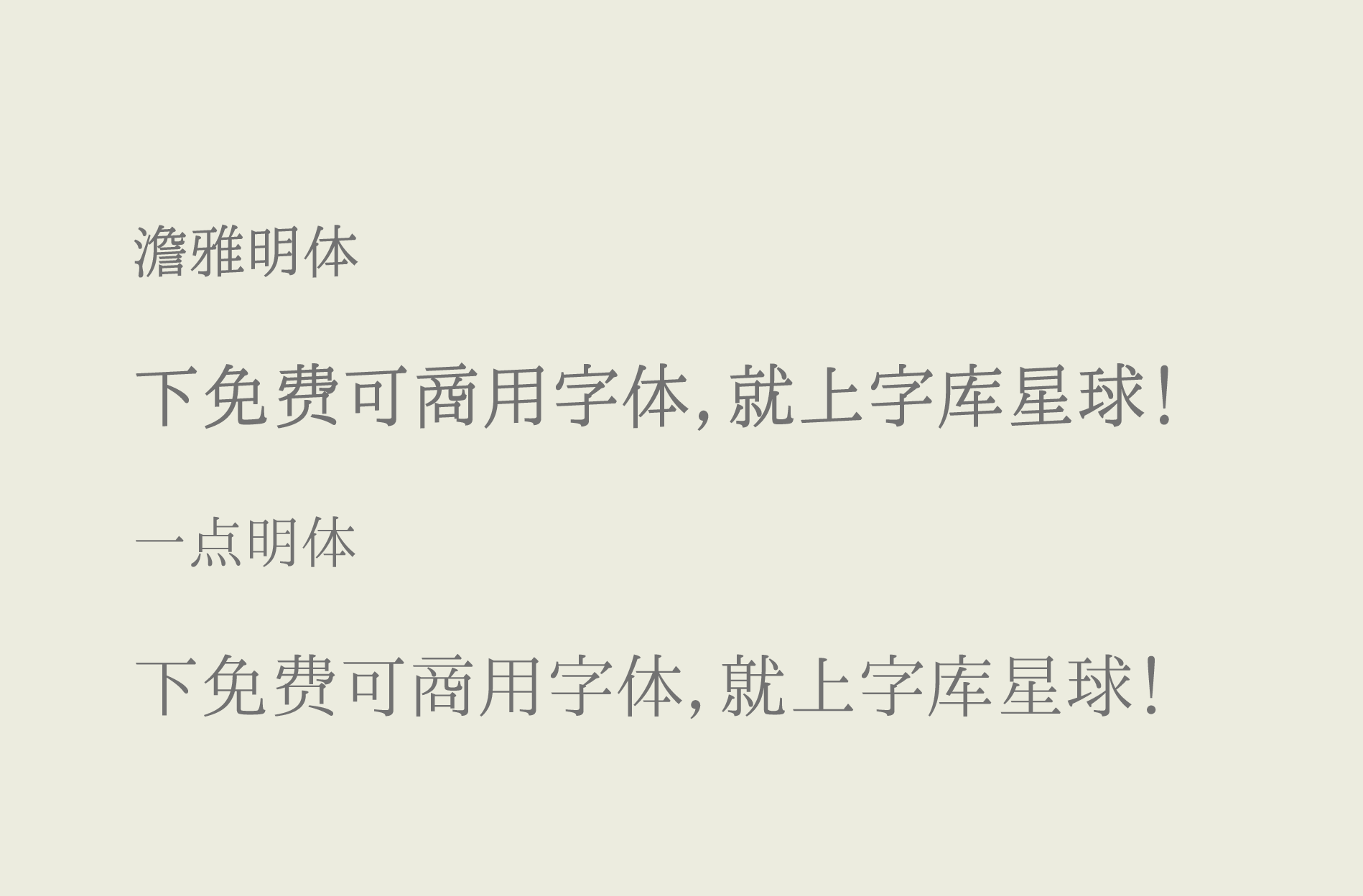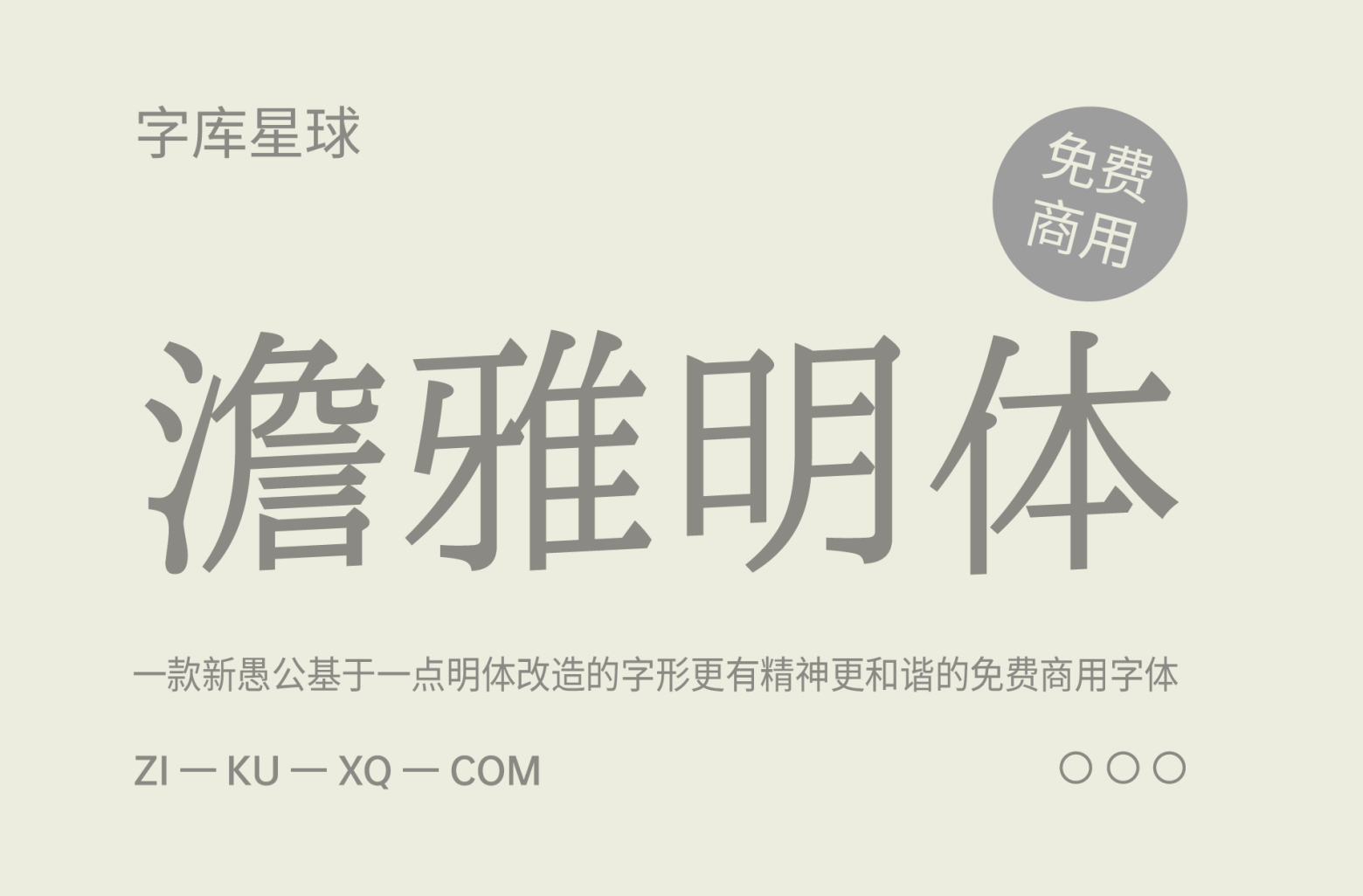
澹雅明体
澹雅明体是一款@新愚公基于一点明体改造的字形更有精神更和谐的免费商用字体。名片的方寸之间,见惯标准简体,是否早已产生了视觉疲劳?用一用传承字型(繁体)吧,或许能成为一股清流。
澹雅明体与一点明体的不同之处是,一点明体笔画较细,而澹雅明体把一点明体的笔画进行加粗,使明体字形更有精神,看上去更和谐。
澹雅明体分为三个样式,分别为澹雅明体ABC三款。“澹雅明体A”可用于单位名称,“澹雅明体C”可用于职务,“澹雅明体B”可用于地址、电话等。有VI诉求的可忽略。
下面是澹雅明体与一点明体的对比效果图:
澹雅明体